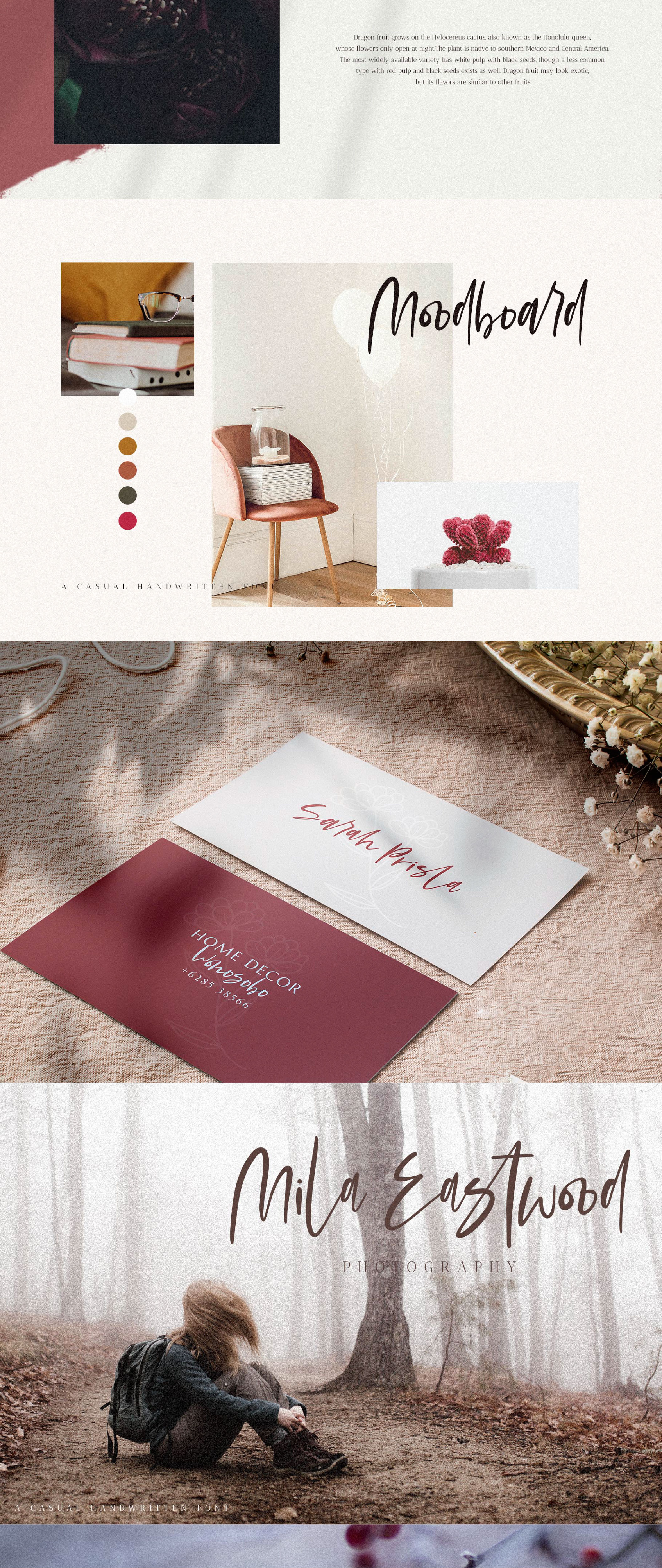
一个时尚及休闲手写字体,Mondela ||休闲手写字体
嗨,引入新的Mondela随意手写字体!对于那些你谁是需要一个淡淡的优雅,别致与现代为您的设计,这种字体是为你创造!
它包括全套大写和小写字母,多语种符号,数字,标点符号和23个连字。
这是巨大的多功能和真正的手写标识与品牌,广告文本,报价,标题和产品包装的理想选择。